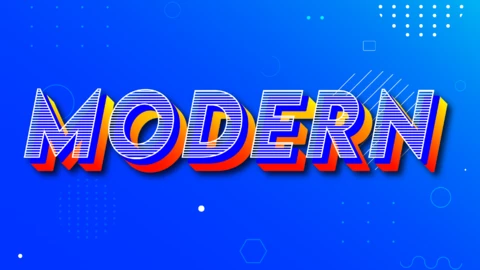
Современный и красочный текстовый эффект, который можно менять
Lemon Milk Font Эффект текста
Создание текстового эффекта "Lemon Milk Font" Современный и красочный текстовый эффект, который можно менять с помощью нашего онлайн-генератора пользовательских шрифтов.